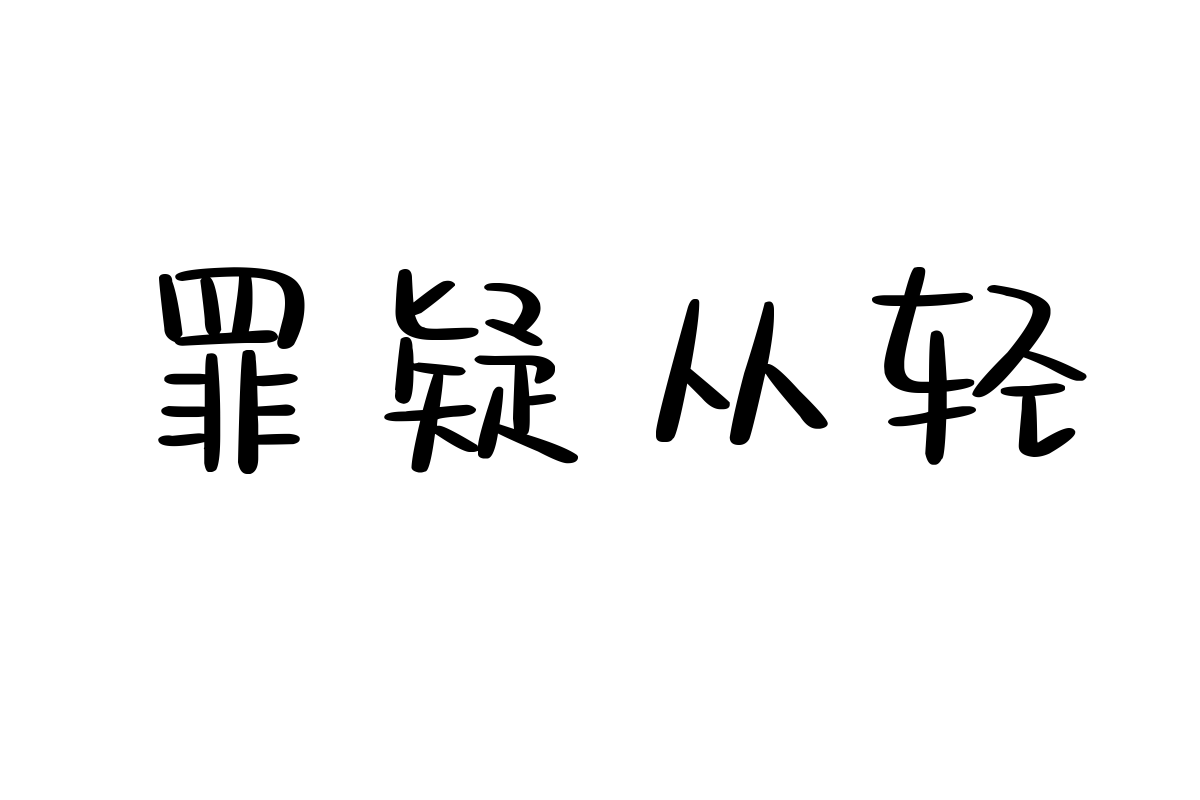
也字工厂曲奇体是一种独特的字体,它由设计师精心打造而成。这种字体的特点是字形独特、线条流畅,给人一种轻松愉悦的感觉。它的笔画粗细适中,既有力度又不失灵动,非常适合用于标题、正文等文字内容。
也字工厂曲奇体采用了独特的曲奇造型设计,使得每个字符都呈现出独特的视觉效果。这种字体不仅适合用于印刷品,还适合用于网页、手机屏幕等数字媒体上,能够为各种应用场景增添一份独特的魅力。